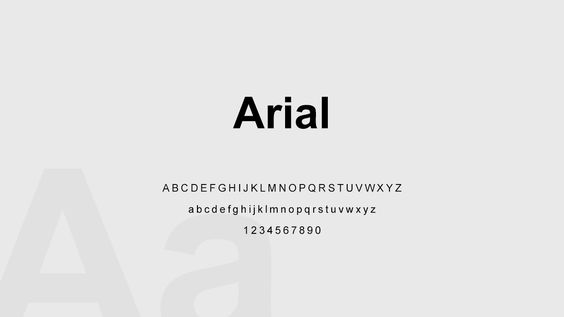
Tác giả: Robin Nicholas, Patricia Saunders
Ngày phát hành: 1982
Ngôn ngữ: Tiếng Anh, Tiếng Việt
Bộ Font: Arial
Phân loại: Đa dạng
Arial Normal Opentype Truetype Font là một phông chữ phổ biến và linh hoạt, được sử dụng rộng rãi trong nhiều ứng dụng nhờ vào tính dễ đọc và khả năng tương thích cao. Arial Normal Opentype Truetype là một font chữ thuộc bộ font chữ không chân. Với thiết kế đơn giản nhưng thanh lịch, phông chữ này phù hợp cho cả nội dung văn bản dài và các tiêu đề ngắn gọn, giúp truyền tải thông điệp một cách rõ ràng và hiệu quả. Đặc biệt, với các định dạng Opentype và Truetype, Arial Normal đảm bảo chất lượng hiển thị vượt trội trên mọi nền tảng, từ in ấn đến kỹ thuật số, mang đến cho bạn một lựa chọn phông chữ đáng tin cậy và chuyên nghiệp.